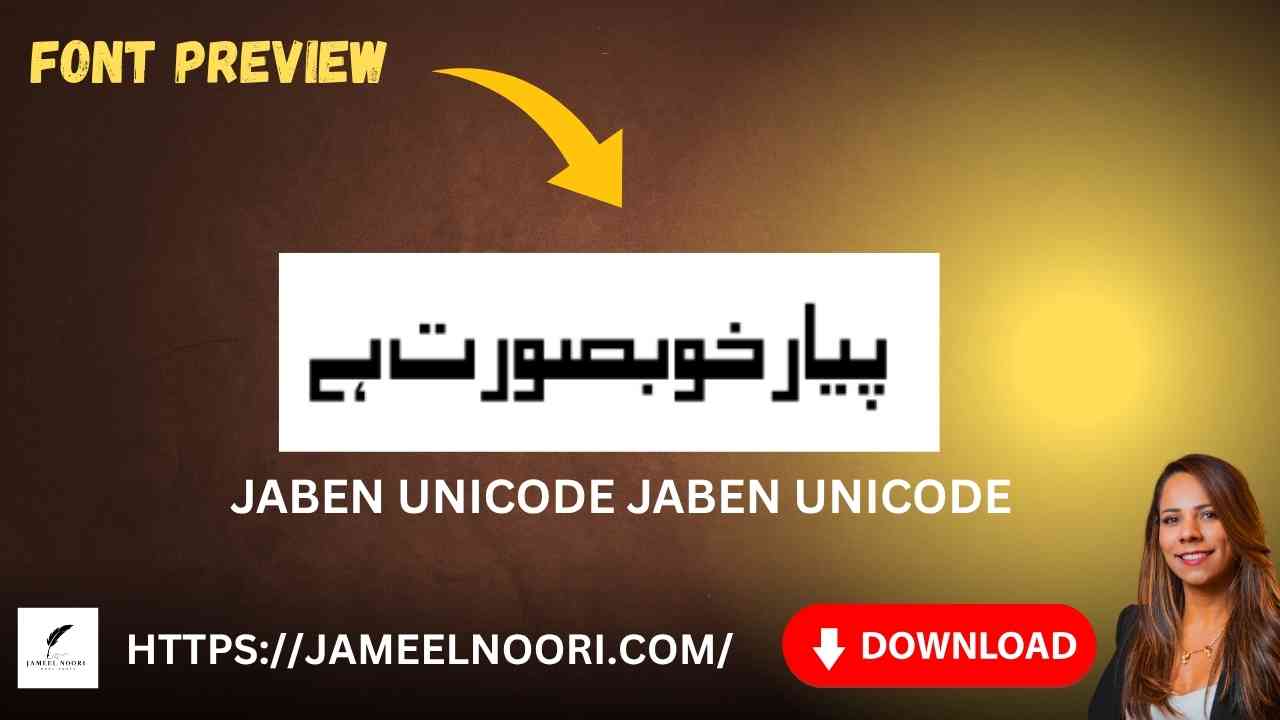
What is Jaben Unicode Font?
Jaben Unicode ek popular aur versatile Urdu TrueType font hai jo Unicode standard ko follow karta hai. Yeh font regular style mein available hai aur har type ke Urdu text ke liye best hai. Jaben Unicode ko designers, students, publishers, aur content creators bohat use karte hain.
Why Download Jaben Unicode Font?
Jaben Unicode font ko khas banane wali kuch important features hain:
1. Unicode Compliant
Yeh font Unicode standard ko follow karta hai, is liye yeh Windows, Mac, Android, iOS, aur Linux — sab platforms par kaam karta hai. Kisi special software ki zaroorat nahi.
3. Versatile Usage
Jaben Unicode har type ke project mein use kiya ja sakta hai — documents, web design, graphic design, social media, aur video editing.
6. Perfect for Beginners
Agar aap Urdu fonts ke beginner hain to Jaben Unicode best choice hai. Yeh simple, clean, aur readable hai.